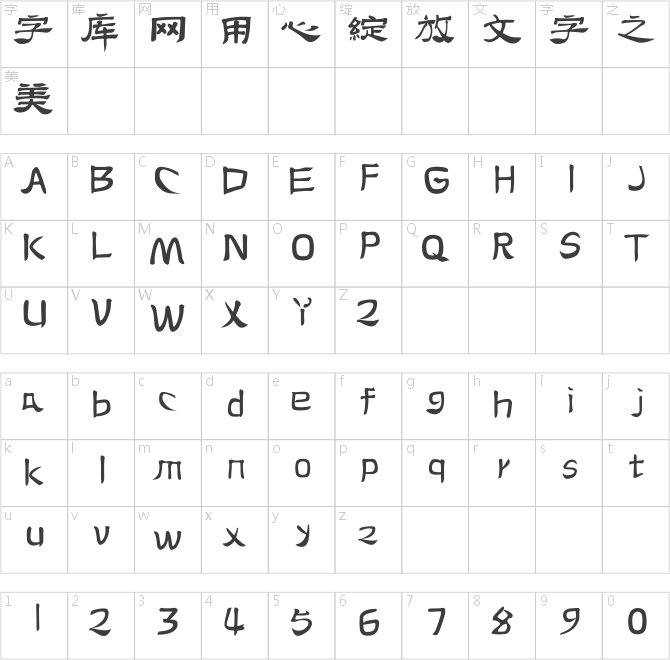
字體名稱: 逐浪?;韬顫h簡
逐浪?;韬顫h簡隸書
2011年,江西南昌出土了驚世的漢代海氏侯古墓群,這是我國有史以來最重要的考古挖掘成果之一。
2005,南昌郊區的海昏侯漢代墓考古發現正式向外布宣傳,震驚業界。
隨著江西南昌漢代?;韬钅箍脊虐l掘出了一批竹簡 這批竹簡被寄予厚望,被認為是整座海昏侯墓出土的最重要文物之一 其中就包含失傳1800年的《論語》知道篇。
為了更好的恢復這一文化,逐浪軟件團隊根據披露的竹簡文字,進行復古與再制,實現現代字庫的制程,使用數字技術,真實呈現西漢文字。
字體創作原則:
1、  完全遵從出土字簡構字。
2、  復古,而不泥古,針對現代漢字橫排進行優化,同時保留豎排的形式感。
3、  基于現代字庫進行優化。
基于GB2312標準,同時加入逐浪生僻字專用庫,為傳統與現代,架接橋梁。
恢宏古文化,傳播文明,這正是逐浪軟件和逐浪字庫研發團隊孜孜以求的使命。
源自國家高新科技企業-逐浪軟件團隊的精品力作,首次將漢代皇家字體發布,以現代中文字庫形式為為全球文明提供奉獻,傳承文明,逐浪啟航。